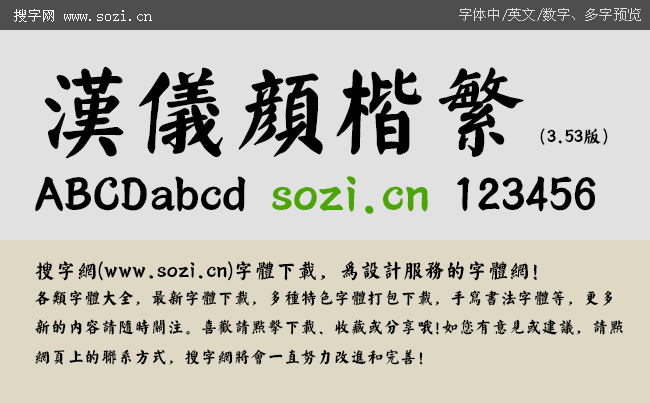
漢儀顏楷繁3.53版
搜字網(wǎng)給大家提供一款漢儀顏楷繁3.53版中文書(shū)法字體下載。顏楷的筆型厚實(shí)有力,字構(gòu)平穩(wěn)扎實(shí),具有濃厚的書(shū)法氣息,適合包裝設(shè)計(jì)、海報(bào)設(shè)計(jì)、畫(huà)冊(cè)設(shè)計(jì)等廣告設(shè)計(jì)場(chǎng)合使用。